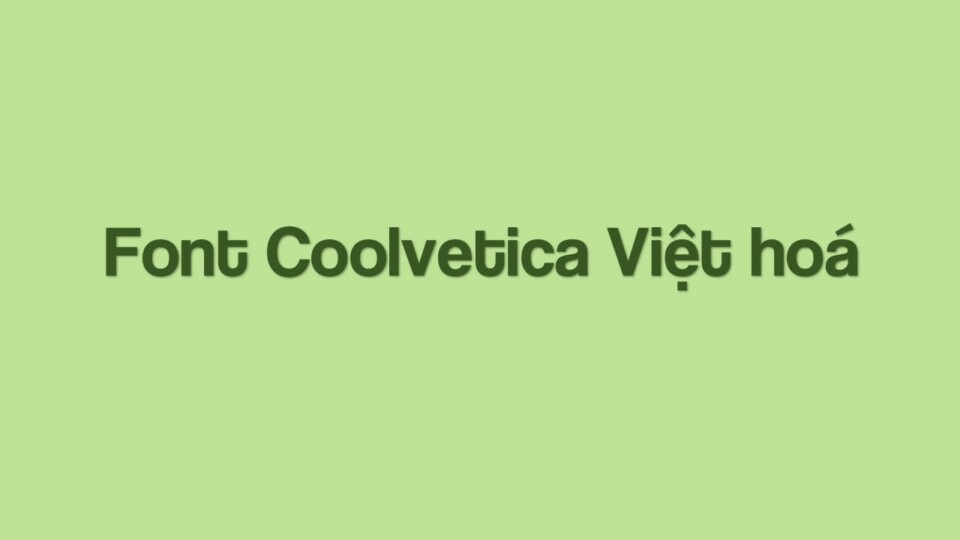
Font việt hóa Coolvetica – Bộ Font Sans Serif Đẳng Cấp Cho Thiết Kế Hiện Đại
Giới thiệu về Font việt hóa Coolvetica trong thiết kế đồ họa
Trong thế giới sáng tạo, việc lựa chọn Font Chữ phù hợp đóng vai trò then chốt để truyền tải thông điệp hiệu quả. Font việt hóa Coolvetica là một biến thể độc đáo dựa trên phong cách Helvetica kinh điển, mang đậm hơi thở của những năm 1970. Với các đường nét bo tròn mượt mà và khoảng cách giữa các chữ cái hẹp, bộ font này tạo nên cảm giác hiện đại, trẻ trung nhưng không kém phần chuyên nghiệp. Phiên bản việt hóa giúp các nhà thiết kế tại Việt Nam dễ dàng sử dụng trong các dự án mà không lo lỗi hiển thị dấu câu.
Tại sao Font việt hóa Coolvetica lại được ưa chuộng?
Lý do chính khiến Font việt hóa Coolvetica trở nên phổ biến là khả năng ứng dụng linh hoạt. Bộ font này cực kỳ phù hợp cho việc thiết kế logo, tiêu đề bài viết hoặc các ấn phẩm quảng cáo cần sự nổi bật. Với phong cách tối giản nhưng mạnh mẽ, Coolvetica giúp nội dung của bạn dễ đọc và thu hút ánh nhìn ngay từ giây phút đầu tiên. Đối với học sinh và sinh viên, đây là công cụ đắc lực để trình bày slide thuyết trình hoặc làm báo cáo một cách chuyên nghiệp nhất.
Để tối ưu hóa vẻ đẹp của Font việt hóa Coolvetica, bạn nên kết hợp nó với các font chữ không chân khác hoặc font chữ có chân mảnh để tạo sự tương phản. Khi trình bày văn bản, hãy chú ý đến khoảng cách dòng để giữ cho bố cục luôn thoáng đãng. Việc cài đặt cũng rất đơn giản, bạn chỉ cần tải tệp định dạng .ttf hoặc .otf, sau đó cài vào hệ thống máy tính để sử dụng trên các phần mềm như Word, Canva hay Photoshop.